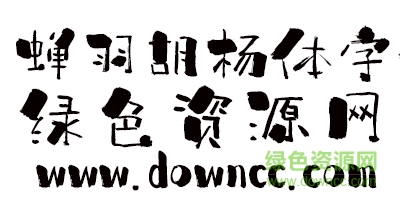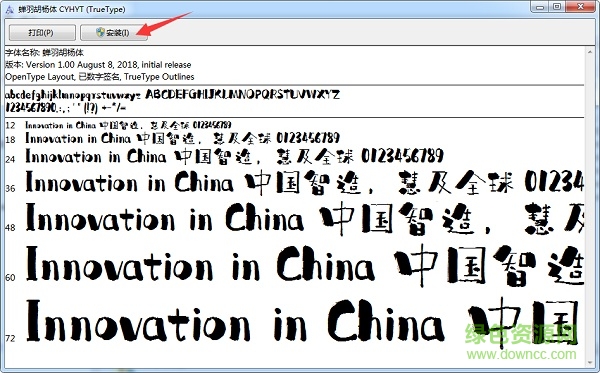
蟬羽胡楊體字體是一個非常美觀的藝術(shù)字體。是蟬羽字體系列中外形最為特別的一款字體!看起來有點(diǎn)毛筆字的效果,在設(shè)計(jì)行業(yè)使用的非常多!歡迎用戶來綠色資源網(wǎng)下載使用。
蟬羽胡楊體內(nèi)外空間布局均勻,筆畫遒勁靈動,連筆張弛有度,結(jié)體清麗優(yōu)美,能夠應(yīng)用于文本裝潢、信息展示、網(wǎng)頁設(shè)計(jì)、篆刻制模、數(shù)據(jù)制作、裝潢設(shè)計(jì)、計(jì)算藝術(shù)設(shè)計(jì)、視覺設(shè)計(jì)、字帖等一切合法應(yīng)用場景!
字體全稱:蟬羽胡楊體,常規(guī)
字體風(fēng)格:Regular